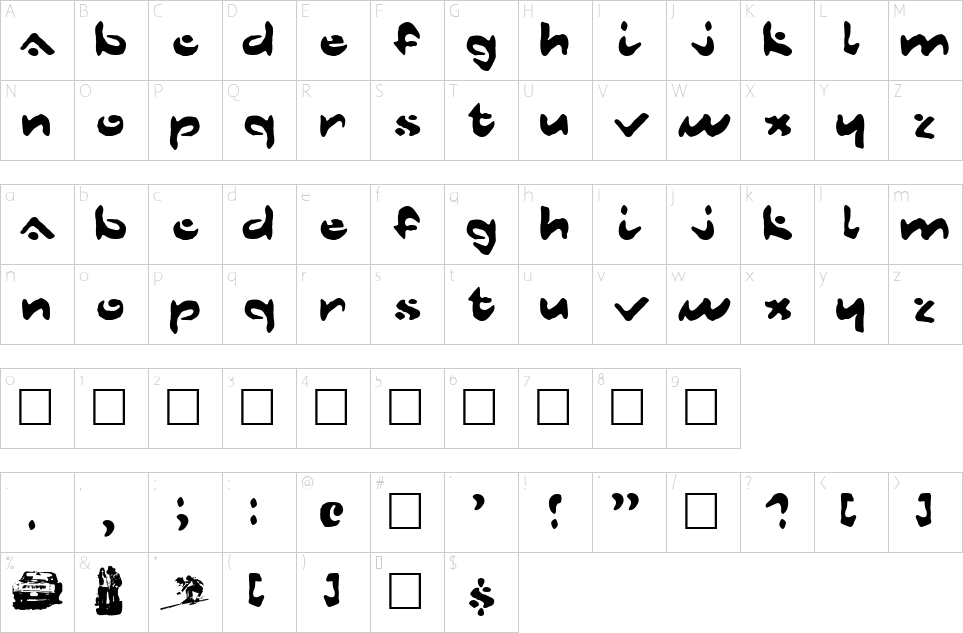
A Dust Mites é uma elegante e minimalista fonte que ganha vida graças ao design cuidadoso dos designers Kejak. Esta opção gratuita não apenas oferece funcionalidades versáteis, mas também traz um ar de sofisticação a qualquer projeto, seja ele digital ou impressão. Se você busca uma fonte que complementa suas ideias de maneira natural e envolvente, a Dust Mites é definitivamente o caminho para você. Ainda não experimentou? Recomendamos baixar agora, já que esta font foi baixada mais de duas mil vezes pela comunidade digital. Seja um deles!